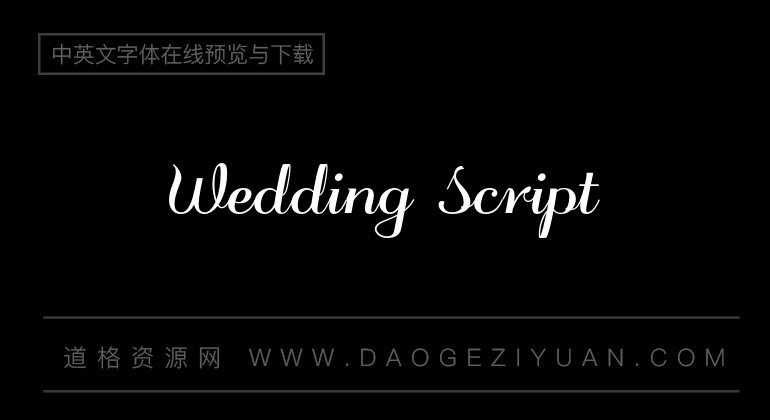
Wedding Script
? Wedding Script 是一款浪漫的手写字体,具有温柔、优雅和浪漫的特点。它有着清新的曲线,柔和的笔画,以及一个简洁的设计。它可以用来制作婚礼邀请,婚礼礼品,婚礼仪式,婚礼装饰品等。它的字体特点使它非常适合用来制作浪漫的婚礼印刷品,以及其他浪漫的主题装饰品。
Wedding Script是一款非常不错的手写艺术字体,具有很好的视觉感,适合于文化类的宣传设计、商业类品牌的广告和产品包装设计以及个性化文字排版等较多场景。